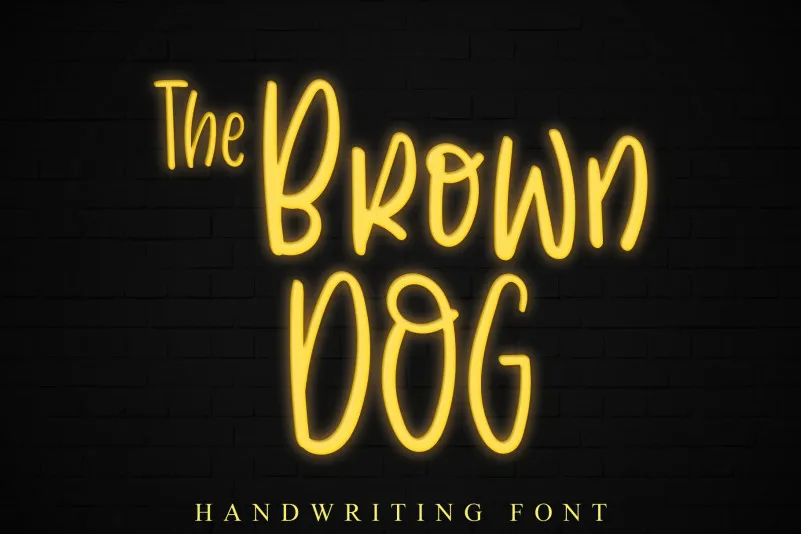
Aqui está uma descrição criada com base nas regras fornecidas: A fonte ‘The Brown Dog’ é um estilo manual e descontraído, perfeito para dar um toque divertido aos seus trabalhos de design. Esta fonte tem linhas limpas e um ar um pouco esquisito que a torna ideal para criar logomarcas, marcas de marca e projetos DIY criativos em redes sociais. Com certeza uma opção ótima para quem quer dar um toque único ao seu trabalho sem comprometer o design clássico e limpo que tanto apreciamos na nossa identidade visual. Ideal para quem valoriza uma sensação descontraída e divertida em suas criações, se prepare para trazer um pouco de encanto para seus projetos com ‘The Brown Dog’.